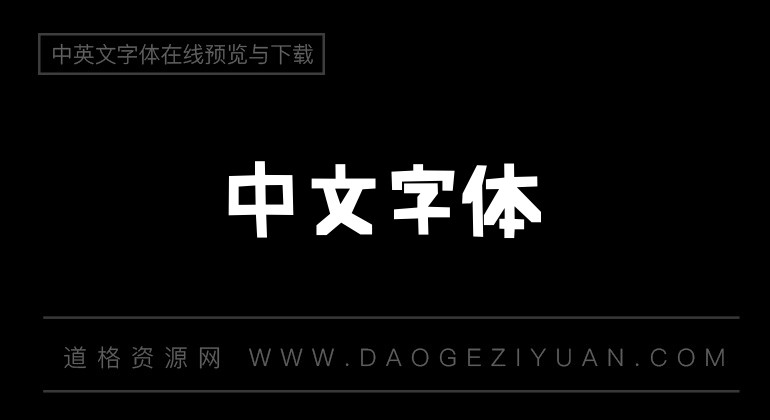
ちはや角
ちはや角字体是一种日本字体,由日本插画家、设计师和漫画家村上真司(Masaki Murakami)设计,采用了清新的角落字体设计,拥有简洁的线条和清新的角度,使字体更加简洁大方。这种字体可以用于报纸、杂志、网站、平面设计等多种场景,可以为文字增添一种时尚感。
ちはや角是一款非常不错的手写艺术字体,具有很好的视觉感,适合于文化类的宣传设计、商业类品牌的广告和产品包装设计以及个性化文字排版等较多场景。
ちはや角字符映射图